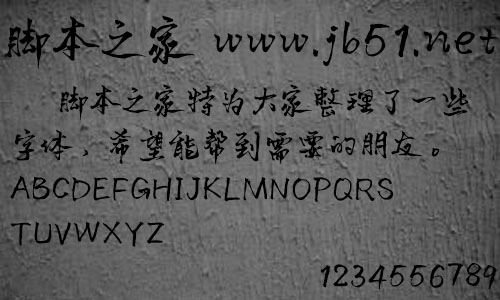
默陌雅詩手跡字體是一款中文手寫字體,該字體筆觸清晰明朗,字體靈動(dòng)飄逸,一撇一捺略顯灑脫之感,具有很好的視覺影響力,適合應(yīng)用于藝術(shù)設(shè)計(jì),平面宣傳設(shè)計(jì)、網(wǎng)頁設(shè)計(jì),書法字帖等領(lǐng)域。需要的朋友可以前來本站下載。